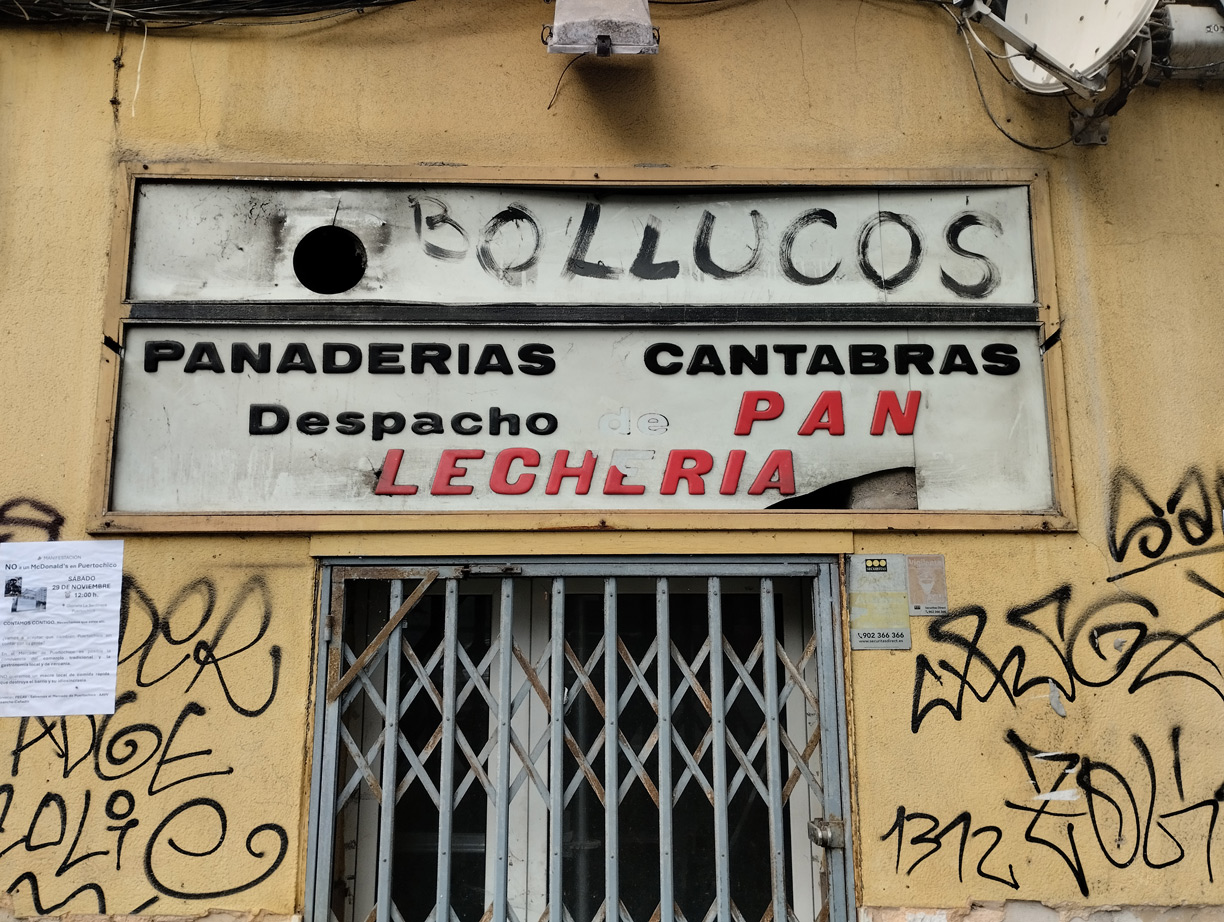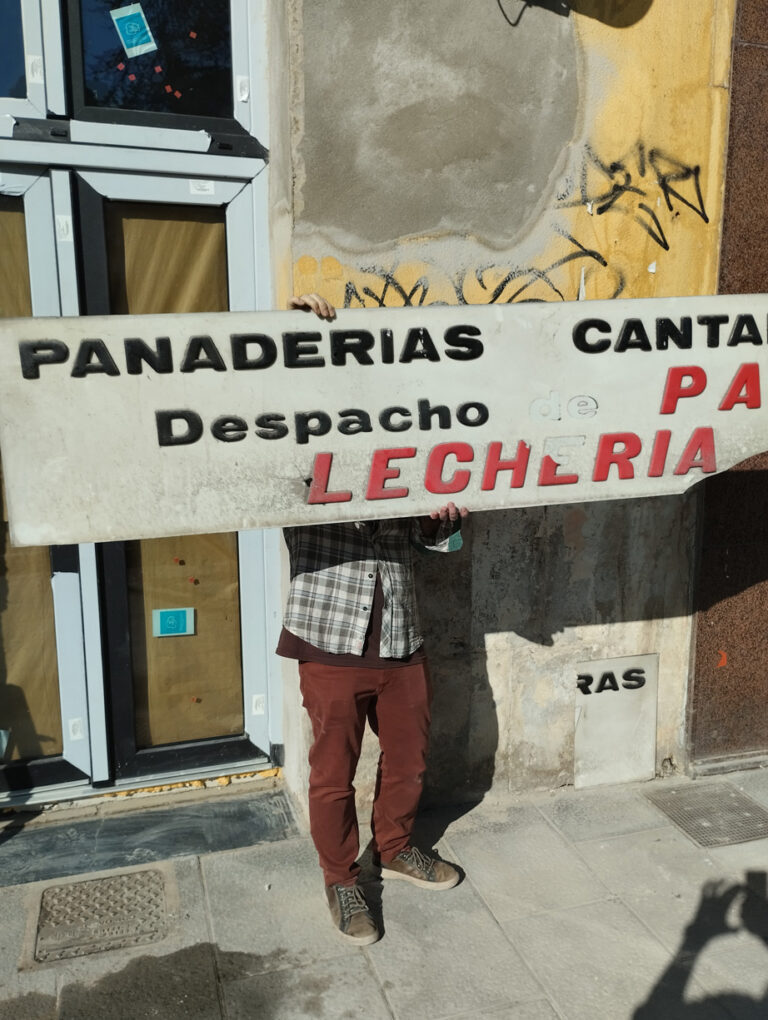
Panaderías Cántabras
En noviembre del año pasado, nos llegó por mensaje que apareció un cartel durante las obras de un local. Lo publicamos en Instagram y otras redes para saber más.
La información que nos llegaba es que era el antiguo obrador de la Panadería Torre, que ocupaba todo el bajo de edificio hace más de 50 años. Con el tiempo se fue achicando hasta, que como puedes ver en el post adjunto el local fue con el tiempo panaderias varias.
Pudimos ir a recoger este cartel, junto con el de «bollucos» gracias a la colaboración de la Cerrajería Parku, que está al lado.